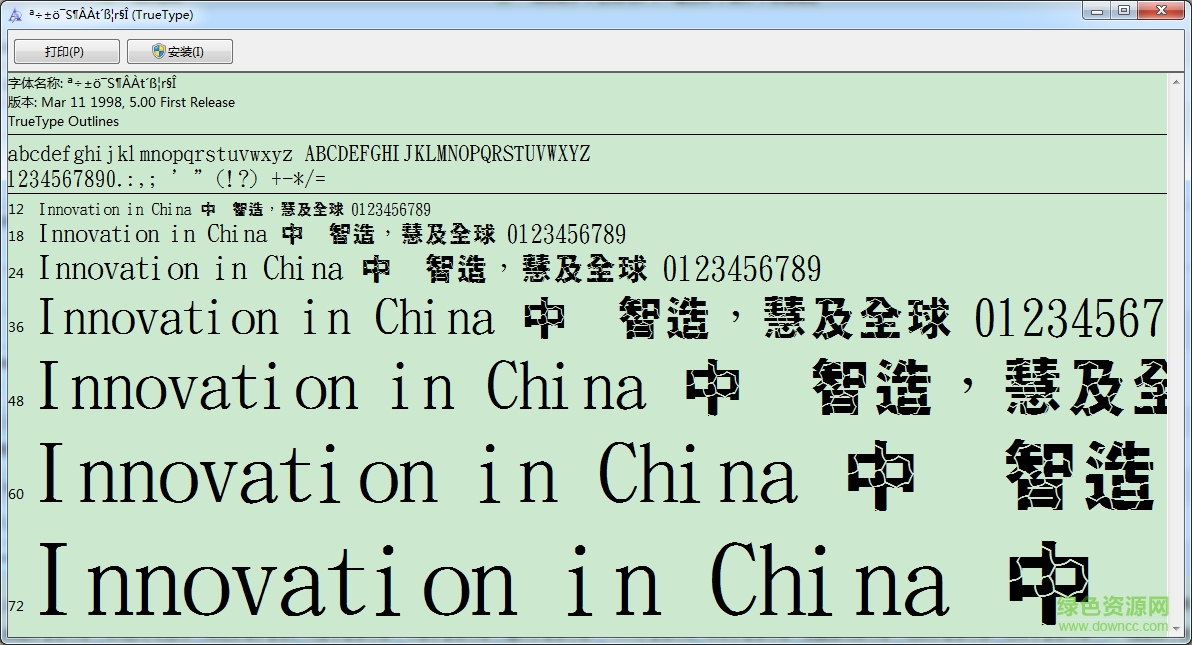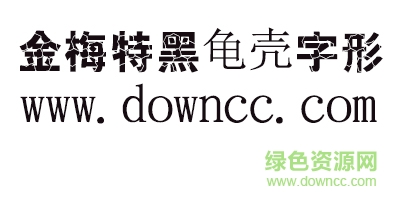
金梅特黑龜殼字形字體是金梅字體庫(kù)中的熱門字體文件。這類風(fēng)格的字體還是很少見的,帶有少許龜殼裂紋,書寫的文字內(nèi)容很突出!多用來設(shè)計(jì)文字內(nèi)容標(biāo)題!快來下載安裝吧。
金梅特黑龜殼字形是一款非常有特色的金梅字體,這款字體帶有裂紋效果,看上去非常的美觀。非常適用于廣告設(shè)計(jì)、平面設(shè)計(jì)、印刷包裝等,喜歡的朋友歡迎來綠色資源網(wǎng)下載體驗(yàn)!